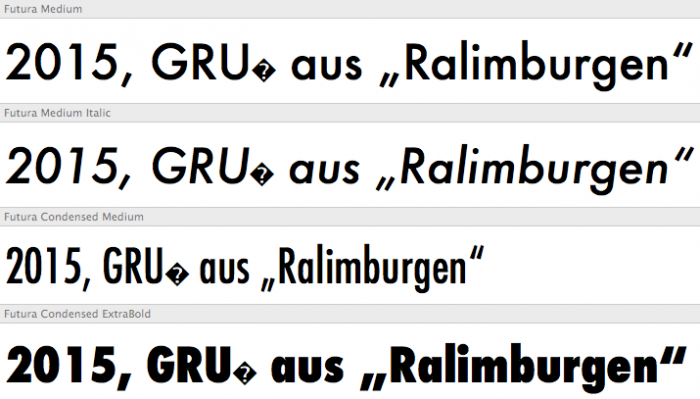
Paratype oder Bitstream?
Wir wollen demnächst Futura kaufen. Wir sind uns aber nicht sicher von welchem Hersteller.
Durch ein einfaches Ausschlussverfahren sind von möglichen (ca.)10 nur 2 übrig geblieben: Futura PT und Futura BT.
Was uns an der Paratype besser gefällt ist der Light Schnitt. Dieser ist bei Bitstream ziemlich fett.
Gibt es irgendwelche Besonderheiten zu den beiden?
und
Gibt es zu der Neufville Digital Version was zu sagen? Das Kerning soll ja nicht so gut sein.
Ich persönliche würde eine aktuelle Schrift kaufen die der Futura ähnelt - das Angebot ist relativ groß. Gefühlt sind die meisten Futura-Versionen schon etwas älter und nicht unbedingt auf dem Stand der Zeit was die technische Seite anbelangt ...
eine sache, die mir aufgefallen ist: bei paratype bekommt ihr für €26 pro schnitt eine menge lateinischer sonderzeichen und das russische alphabet noch dazu. außerdem hat die paratype-variante ein paar opentype-features, mit denen sich zum beispiel proportional zugerichtete ziffern ansteuern lassen, sowie ein (mittelmäßiges) ẞ. bei bitstream bezahlt ihr €29 pro schnitt und kriegt nichts davon. wenn es also unbedingt die futura selbst sein muss, würde ich zu paratype tendieren (obwohl ich die von neufville nie selbst verwendet habe). der gedanke von microboy, einen futura-enkel anzuschaffen, ist aber in jedem fall auch kein falscher.
Futura ist mit der Marke ( Fielmann ) fest verankert.
Eine Alternative zu kaufen fällt somit leider raus.
Das mit den Zeichen bei der Paratype ist mir auch aufgefallen. Was genau meinst du mit "proportional zugerichtete ziffern"?
ziffern können entweder tabellarisch zugerichtet sein (= jede ziffer ist gleich breit) oder proportional zugerichtet (= jede ziffer hat ihre eigene breite). in tabellen sehen proportional zugerichtete ziffern wegen der schwankenden breite oft unruhig aus. in fließtext wirken tabellenziffern oft unharmonisch, weil die (abstände zwischen den) ziffern oft künstlich breiter oder schmaler gemacht werden, um dieselbe breite zu erreichen.
Gibt es zu der Neufville Digital Version was zu sagen? Das Kerning soll ja nicht so gut sein.
Vier Schnitte dieser Version sind im Mac OS X standardmäßig dabei:
Da könnte man sich das Kerning mal genauer ansehen, testen und bei einer Entscheidung dafür ggf. ein paar Euro sparen.
Futura ist mit der Marke ( Fielmann ) fest verankert.
Eine Alternative zu kaufen fällt somit leider raus.
Wenn der Kunde die Schrift bereits vorgibt solltet ihr die Digitalisierung nutzen die Fielmann nutzt und nicht eine "andere" Futura kaufen.
Unter Umständen arbeiten die sogar mit einer Exklusiv-Version – würde bei einem Unternehmen dieser Größe ja Sinn machen und müsste mal recherchiert werden.
In  dem Dokument werden diverse FiFutura-Schnitte verwendet. Fi dürfte wohl für Fielmann stehen dann.
Dann sollte es ja aber auch eine Möglichkeit geben die Schrift direkt von oder über Fielmann zu bekommen.